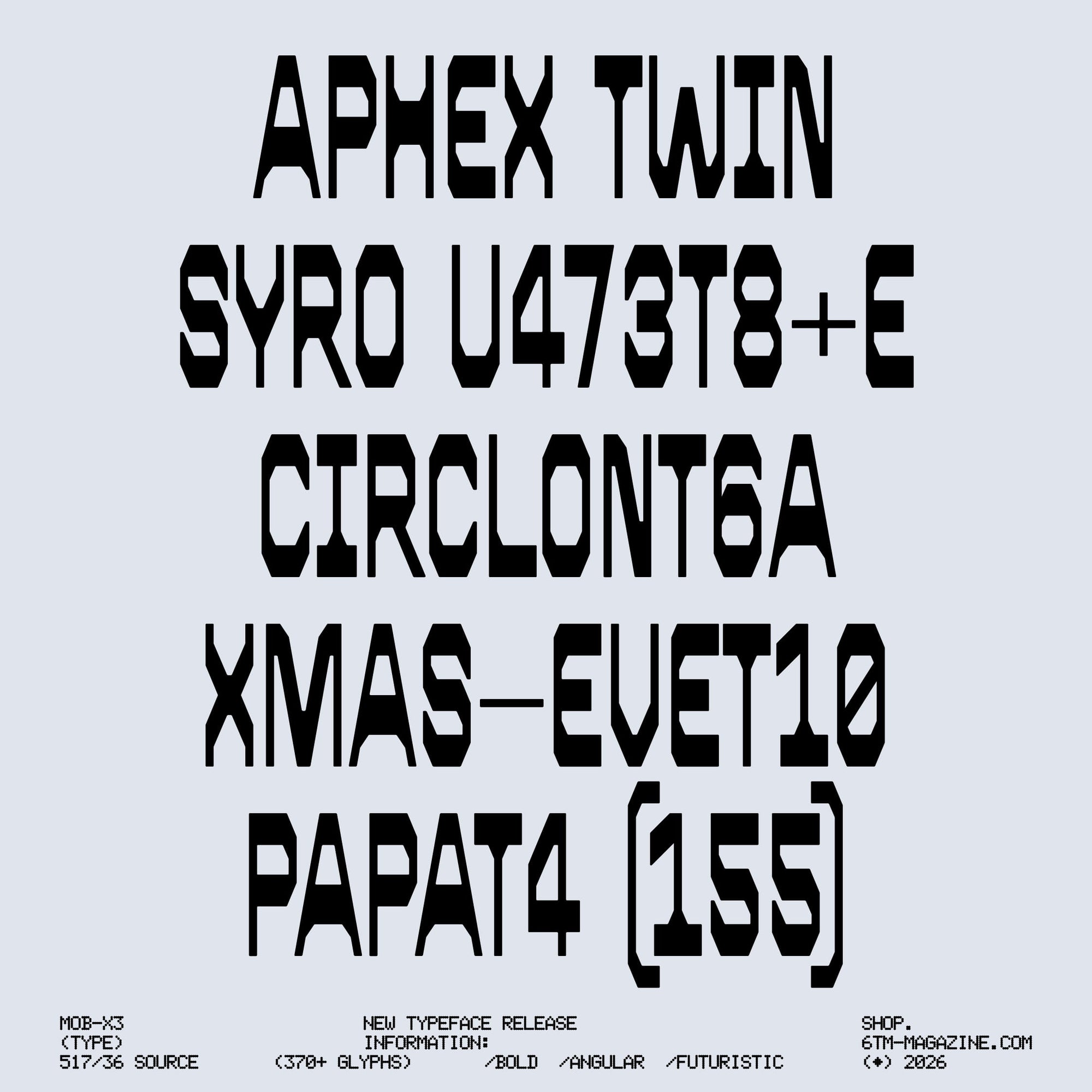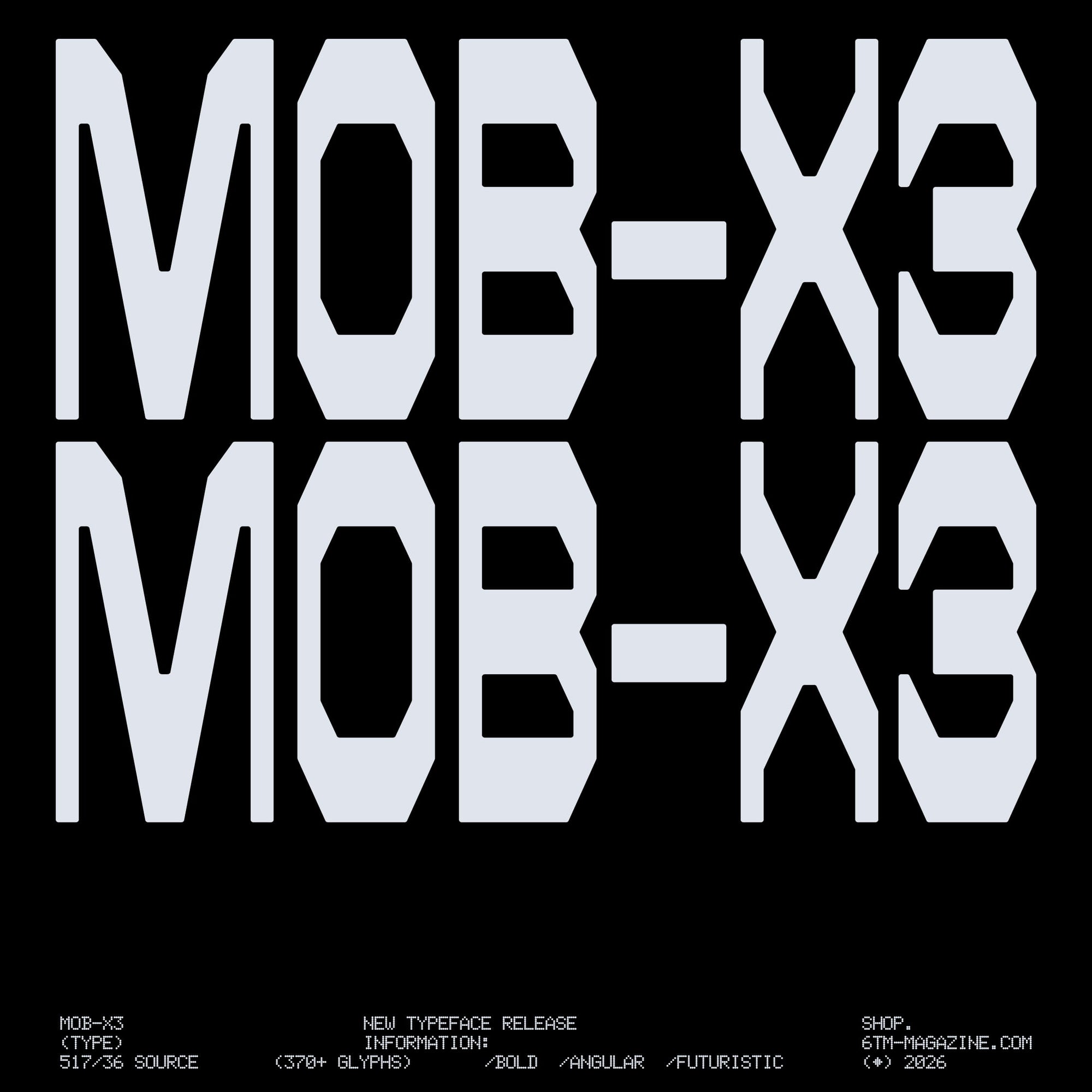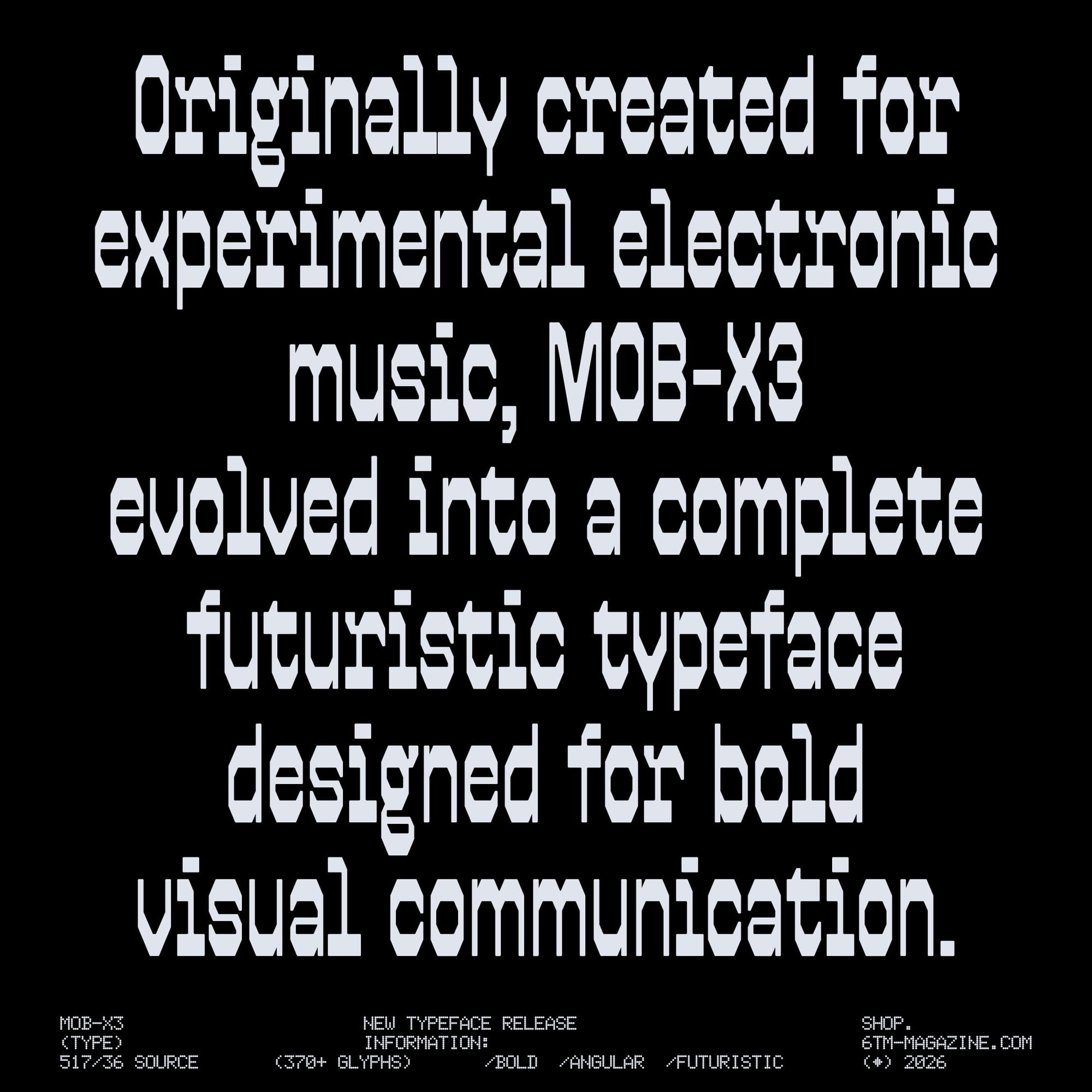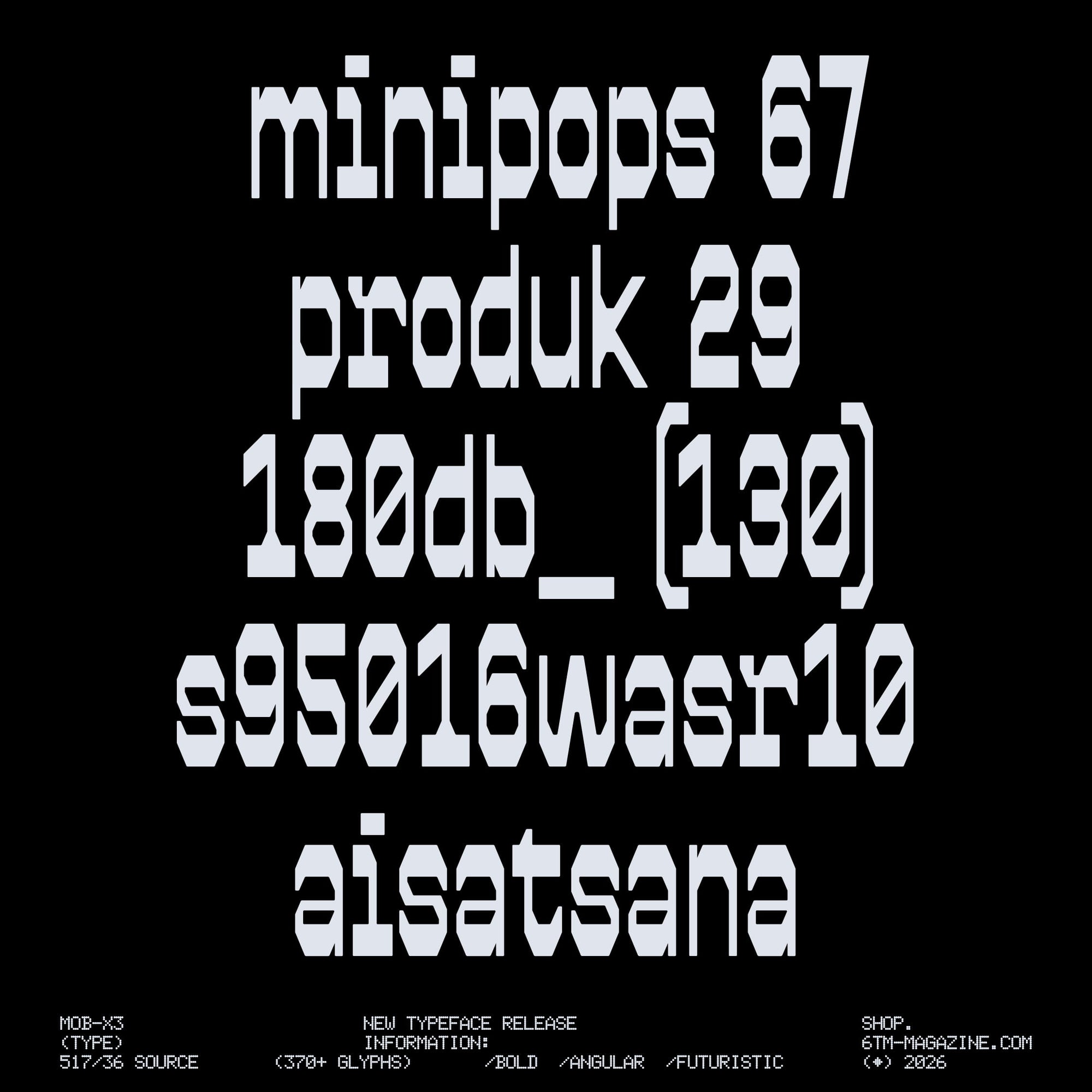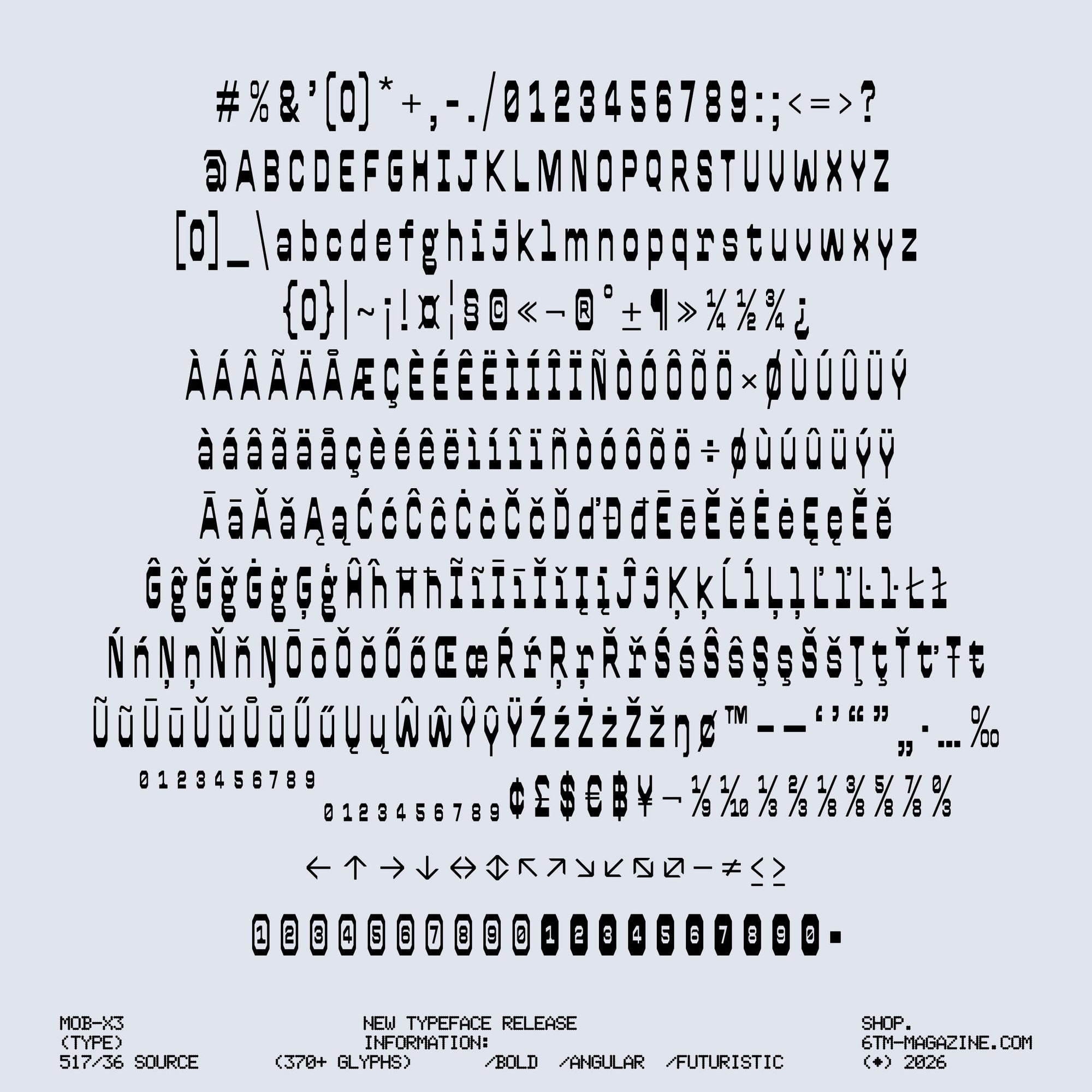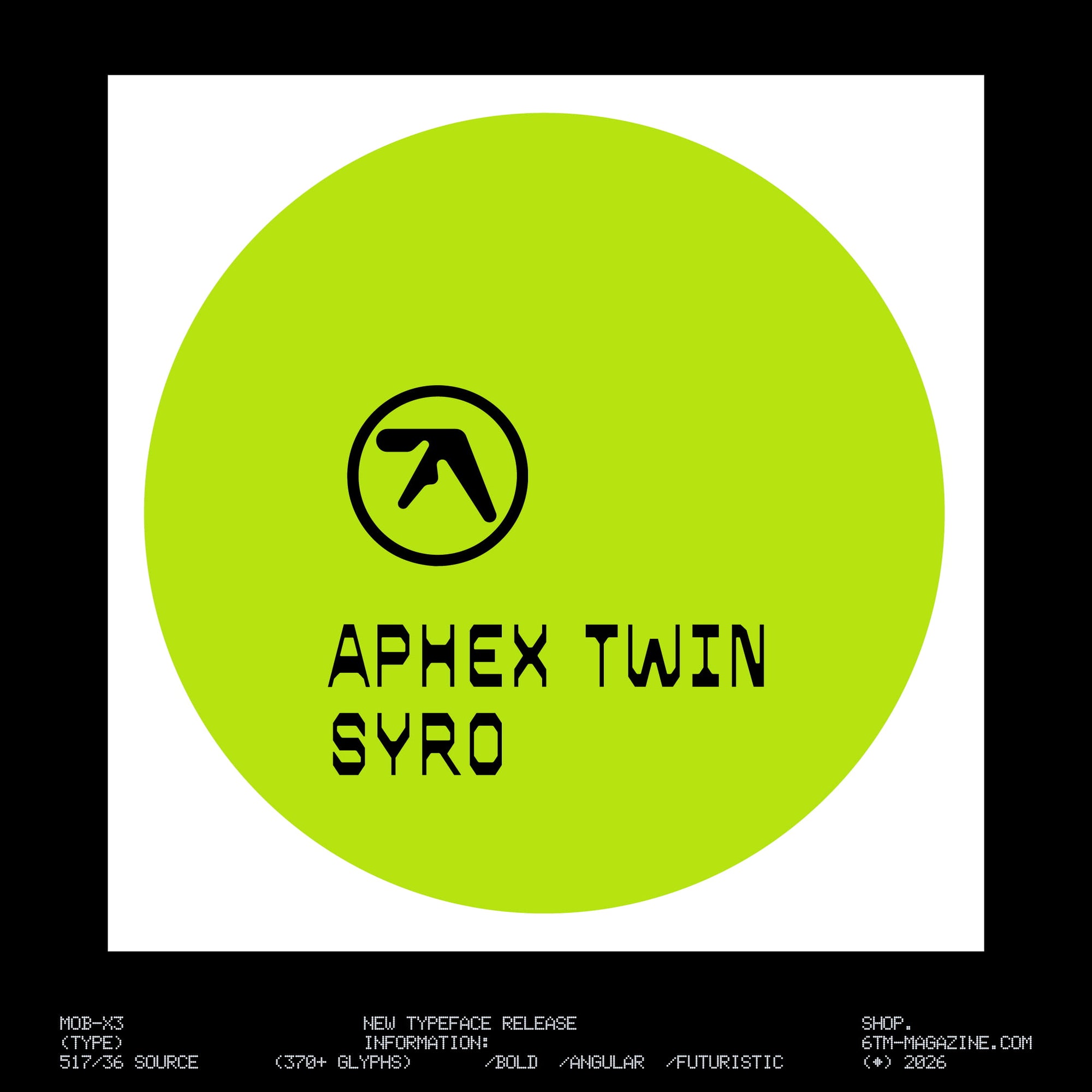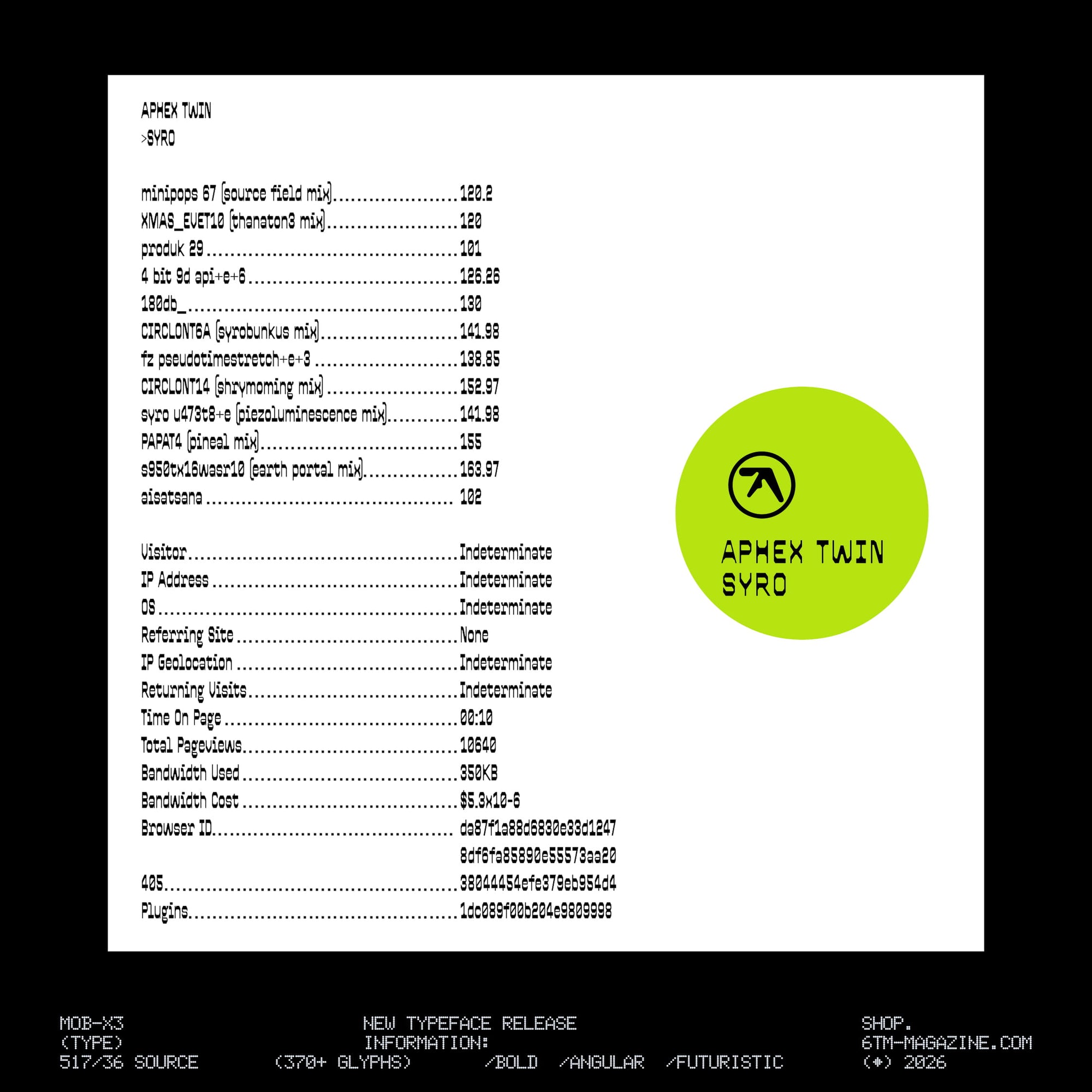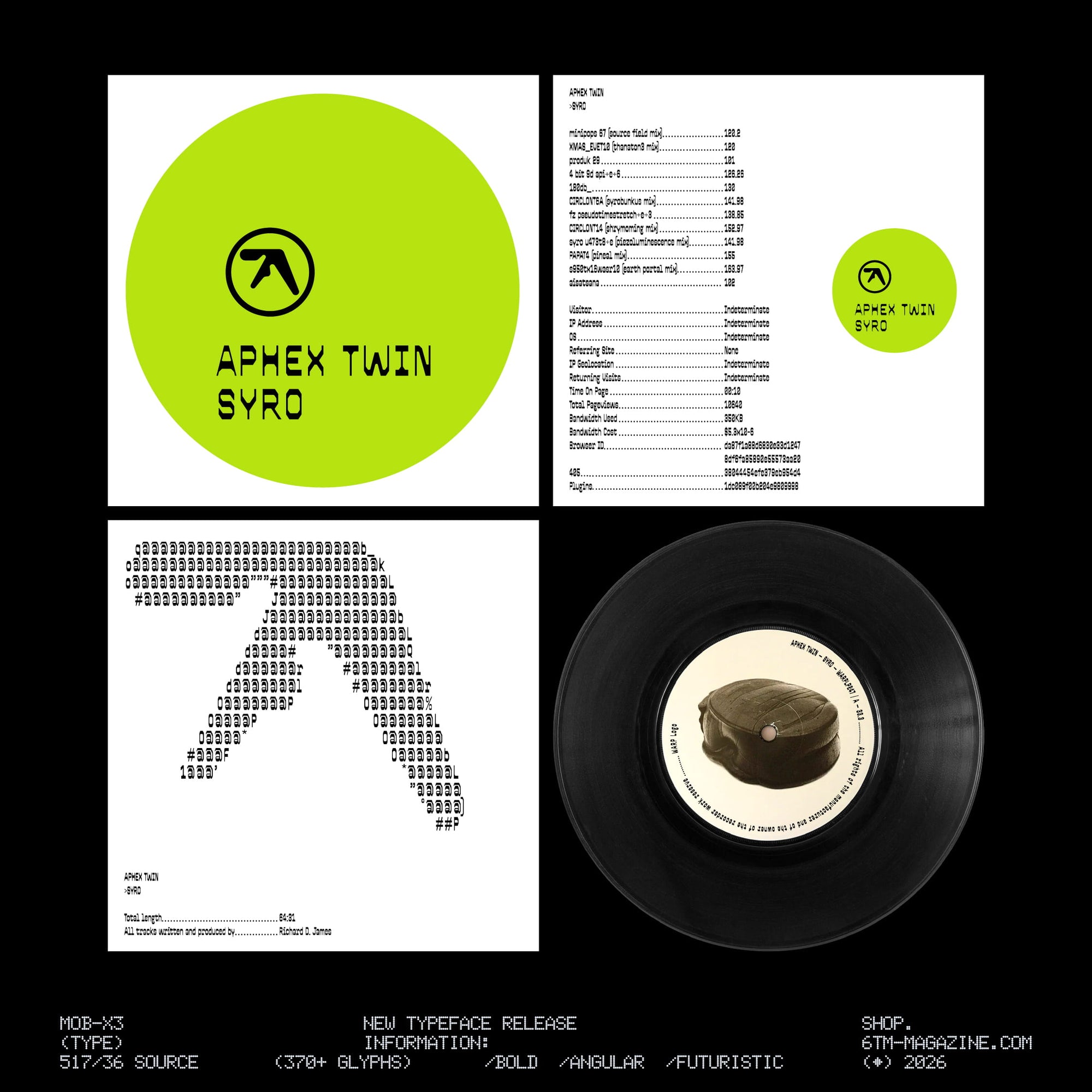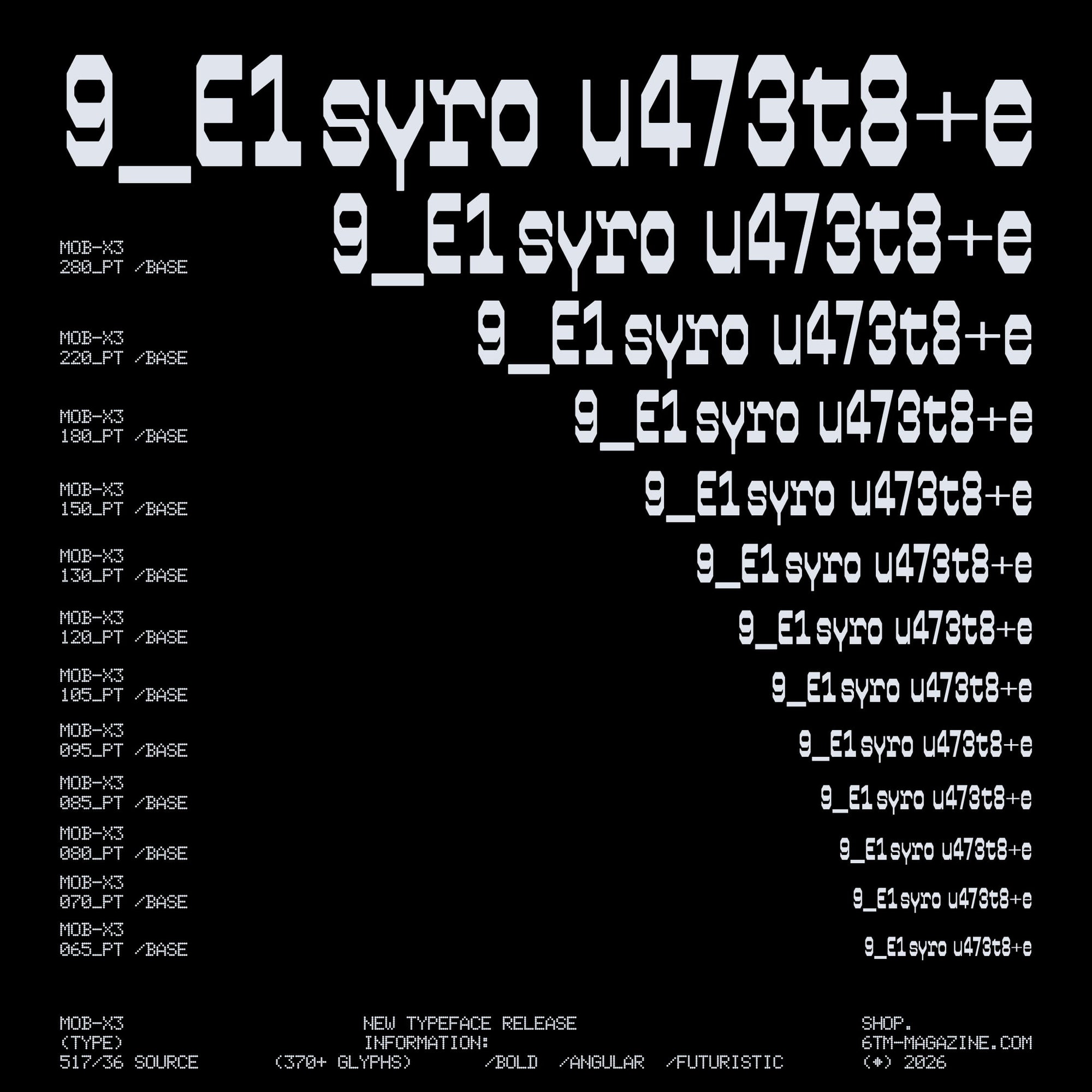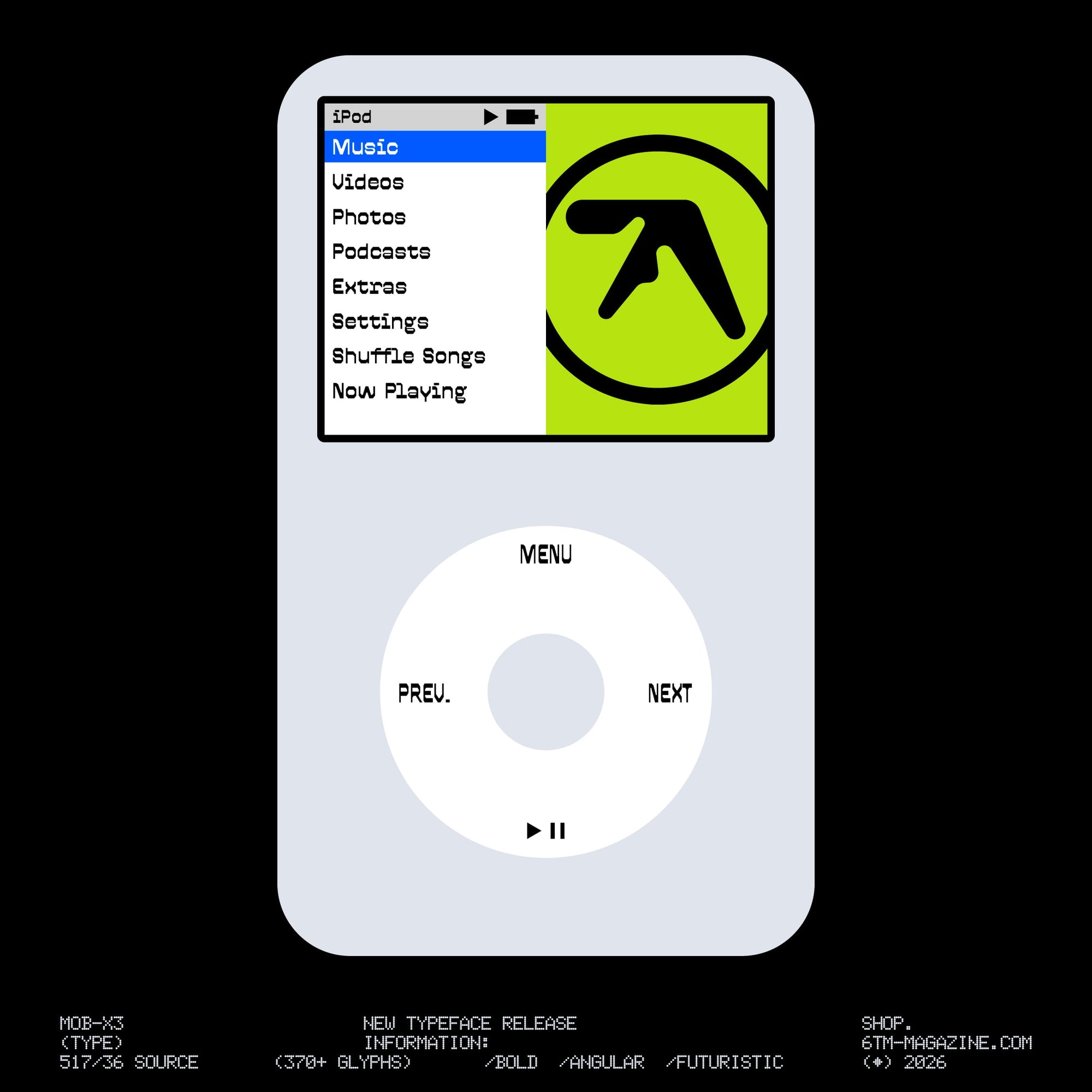
Schriftart MOB-X3
MOB-X3 ist eine Entität, die in unseren Serversystemen verwurzelt ist und sich durch die zeitgenössische digitale Kultur verbreitet. Ursprünglich für experimentelle elektronische Musik entwickelt, entwickelte sich MOB-X3 zu einer kompletten futuristischen Schriftart, die für kühne visuelle Kommunikation entworfen wurde.
Version 1.0 bietet den Stil Regular mit kondensierten, fetten und kantigen Buchstabenformen. Entwickelt, um sowohl im Text- als auch im Display-Bereich zu überzeugen, umfasst sie Klein-/Großbuchstaben, Diakritika, Ziffern, Satzzeichen, Symbole und mehr. MOB-X3 ist ein vielseitiges Werkzeug für Branding, Plakate, redaktionelle Layouts und digitale Projekte mit einer ausgeprägt futuristischen Ästhetik.
Merkmale
• 370+ Glyphen
• Zeichensatz: Lateinisch-Europäisch
• Kleinbuchstaben
• Großbuchstaben
• Diakritika
• Alternativen
• Ziffern (3 Sätze)
• Satzzeichen
• Symbole
• Währung
• Pfeile
• Mathematik